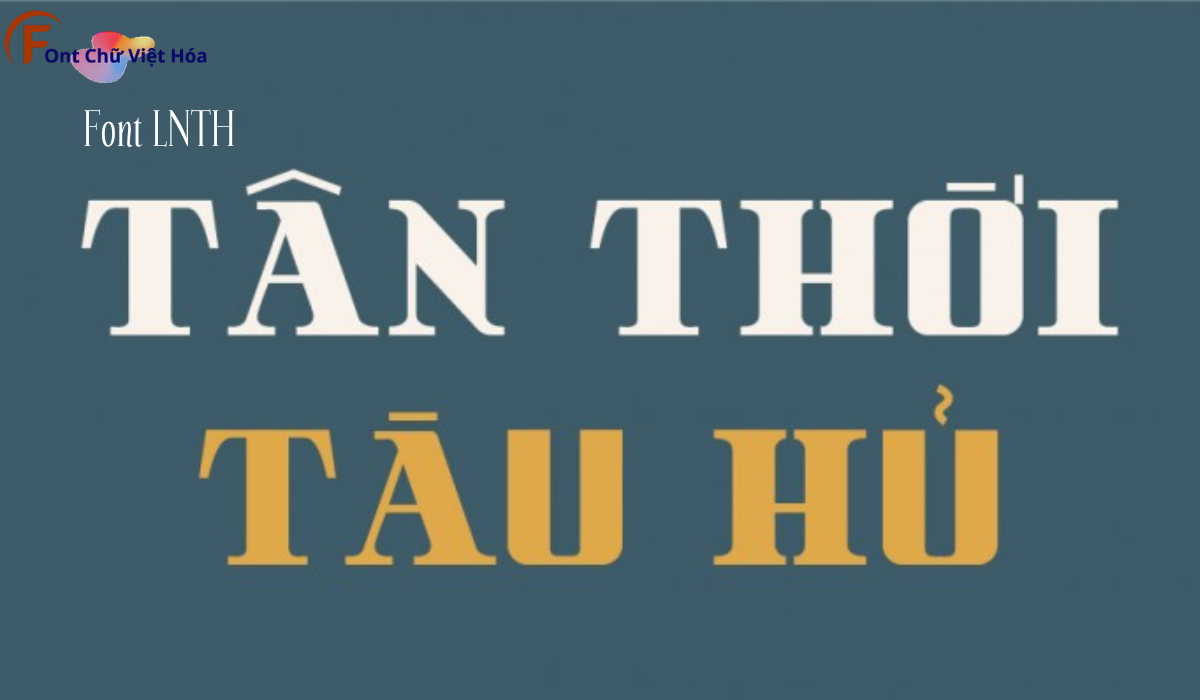
Font LNTH Peter Obscure Việt Hóa
Tác giả: LNTH
Font LNTH Peter Obscure Việt Hóa là một font chữ bí ẩn, thuộc bộ LNTH, với thiết kế độc đáo và lạ mắt. Phong cách của font này phù hợp với các dự án thiết kế cần sự bí ẩn và thu hút, như poster phim, bìa sách, hoặc thiệp mời. Font LNTH Peter Obscure Việt Hóa mang đến sự độc đáo và dễ nhận diện, ứng dụng trong các lĩnh vực sáng tạo. Đặc điểm hình dạng của font bao gồm các đường nét lạ mắt và phức tạp, giúp tăng tính thẩm mỹ và sự chú ý. Việc Việt hóa font giúp người dùng dễ dàng sử dụng trong các thiết kế tiếng Việt, mang lại sự tiện lợi và linh hoạt.